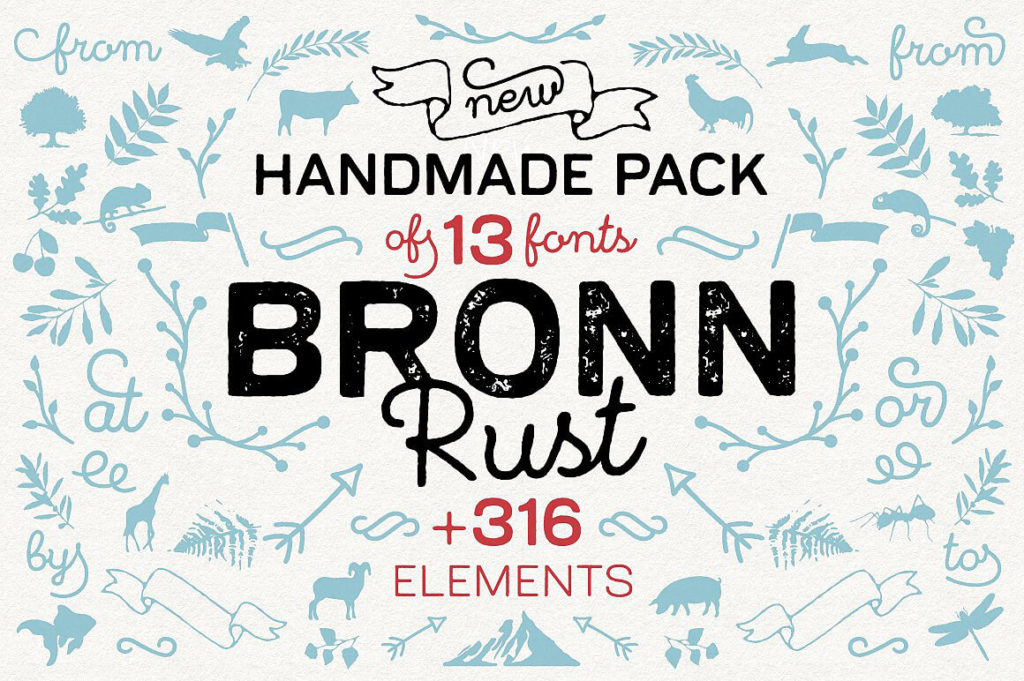
Это уникальный декоративный шрифт с выраженным эффектом «ржавчины» или стекающей жидкости, создающий атмосферу мрачности и грубости. Адаптирован для набора как кириллических, так и латинских текстов. Благодаря объемной структуре букв и нестандартному начертанию, он идеально подходит для акцидентных задач: крупных заголовков, плакатов и рекламных баннеров. Информация об авторе шрифта не найдена, поэтому лицензию рекомендуется уточнять перед использованием в коммерческих проектах. Скачать бесплатно кириллическую версию можно на нашем сайте.